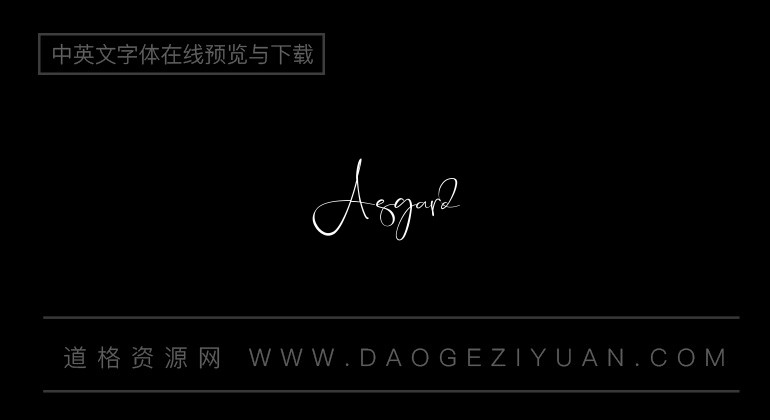
Asgard是一款简洁又美观的字体,它采用了简约的设计风格,可以用于网页、海报、广告、标识和其他印刷品的设计。它的特点是细节设计和精致的几何形状,使字体看起来更加简约、美观、时尚。Asgard字体具有超大的字母,可以清晰地显示出文字的形状,使文字看起来更加清晰、精美。此外,它还具有良好的可读性,可以提高文字的可视性。内容介绍
Asgard是一款非常不错的手写艺术字体,具有很好的视觉感,适合于文化类的宣传设计、商业类品牌的广告和产品包装设计以及个性化文字排版等较多场景。